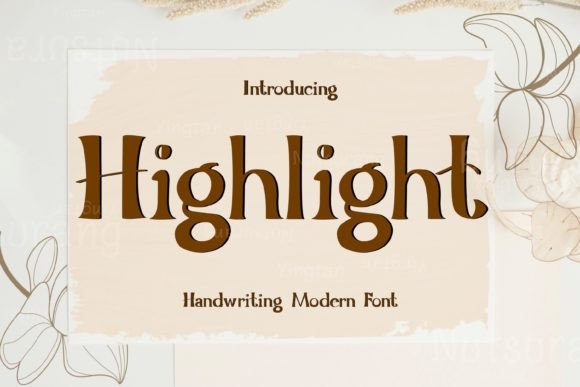
Highlight
Si vous recherchez des ressources de haute qualité comme Highlight, ce pack premium est un choix fantastique pour vos projets créatifs.
Que vous créiez des produits POD (impression à la demande), des invitations de mariage ou des visuels pour les réseaux sociaux, Highlight est un choix idéal.